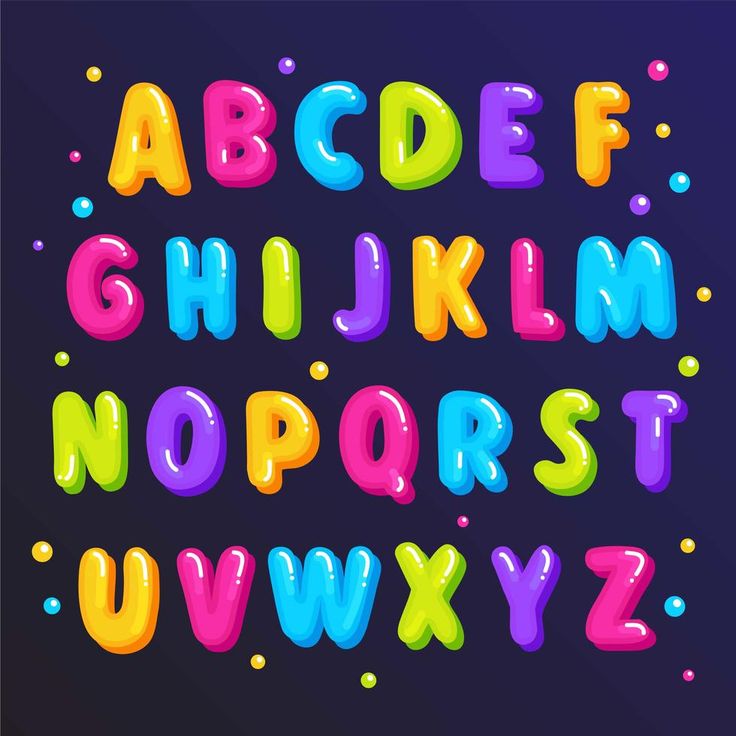
Шрифты цветные: Цветные шрифты для дизайна и оформления
Так что же такое «цветной шрифт»? Это термин, который все чаще появляется и начинает набирать обороты, однако, несмотря на использование в крупных дизайн-проектах он все еще находится в зачаточном состоянии.
Такие производители как Тypekit от Adobe уже начали выпускать некоторые цветовые варианты шрифтов с поддержкой браузера, так что есть некоторое движение в сторону их более широкого использования. Некоторые даже называют цветные шрифты “следующим большим событием в веб-дизайне”.
Сегодня мы рассмотрим ближе данный тренд, и решайте сами, насколько грандиозным он станет. Или наоборот не станет.
Что такое цветной шрифт?
Цветные шрифты практически являются тем, как они называются. Шрифты, состоящие из нескольких цветов, оттенков и градиентов, текстур и прозрачности. Эта шибко модная опция не просто добавляет цвет к буквам и надписям: это специфические шрифты со всеми включенными деталями.
Такие шрифтов могут включать в себя векторную графику, растровые изображения или же то и другое в самом шрифтовом файле, что, в свою очередь, может сделать эти шрифты тяжелее, чем стандартные пакеты шрифтов. Типичные примеры цветных шрифтов включают смайлики или буквы, которые содержат иконки внутри. Одноцветные шрифты в таком стиле часто называют хроматическими шрифтами, потому что они содержат только один оттенок или серый цвет.
Самая большая проблема с цветным шрифтом заключается в том, что нет никакого истинного стандарта его формата.
С другой стороны, основные игроки уже начали принимать рекомендации по использованию таких шрифтов. Mozilla (основа веб-браузера Firefox) и Adobe согласились с тем, что OpenType SVG является предпочтительным форматом; другие же все еще находятся в постоянном движении, когда необходимо прийти к нужному решению.
Как использовать цветные шрифты?
Одна из двух мыслей может возникнуть в вашей голове, когда вы впервые видите цветной шрифт:
- Вау, это ужасно!
- Круто! Я точно знаю, как это использовать!
Независимо от того, к какому лагерю вы относитесь, есть применения, которые идеально подходят для цветных шрифтов. Но вы должны использовать их в разумных пределах, ведь цветные шрифты предназначены для наиболее экономного использования.
Попробуйте цветной шрифт:
- Для техники захвата внимания для короткого слова
- Для элемента значка или логотипа
- Для кавычки перед началом длинного блока текста
- Для дерзкого заголовка в дизайне с минимальным стилем
- Фокусировка на определенном слове или словах в большом блоке текста
- Когда остальная часть дизайна слишком проста
- Когда шрифт будет вашим основным элементом дизайна
- Когда проект требует чего-то забавного и необычного, чтобы привлечь внимание пользователя
Как не использовать цветные шрифты
Существует гораздо больше способов не использовать цветные шрифты, чем вы можете себе представить.
Вы же не хотите в итоге получить мигающий и моргающий веб-сайт с подавляющим цветовым безумием 1990-х годов.
Не используйте цветной шрифт:
- С изображениями или над изображениями
- С забитым задним фоном
- Для большого количества текста
- С множеством других техник дизайна, такими как анимация: обычно одного цвета достаточно для создания визуального воздействия
- С другими новинками или специальными шрифтами
Развитие тренда
Тренд цветового шрифта начинает набирать силу у некоторых крупных игроков в типографике. Формат SVG OpenType, принятый Adobe и Mozilla, может стать инструментом и форматом, который поможет этой тенденции действительно взлетать. Adobe даже недавно добавил цветные шрифты в Photoshop, также вы могли заметить некоторые эмодзи в палитре символов.
Вот как Adobe объясняет OpenType SVG:
«OpenType-SVG — это формат шрифта, в котором шрифт OpenType имеет все или только некоторые его глифы, представленные в качестве изображения SVG.
Это позволяет отображать несколько цветов и градиентов в одном глифе. Из-за этих особенностей мы также ссылаемся на шрифты OpenType-SVG в качестве «цветных шрифтов».
«Шрифты OpenType-SVG позволяют показывать текст с графическими качествами, сохраняя при этом возможность редактировать, индексировать или искать. Они также могут содержать функции OpenType, которые допускают замещение глифа или альтернативные стили глифа».
«Цветные шрифты, такие как Trajan Color Concept и EmojiOne Color, будут отображаться так же, как и обычные шрифты в меню шрифтов ваших программ, но они могут не отображать весь свой потенциал, поскольку многие программы еще не имеют полной поддержки цветовых компонентов. Если ваша программа не поддерживает оформление SVG в шрифтах, глифы возвращаются к простому черному стилю. Цвет может быть применен к этому резервному стилю, поскольку он будет работать как обычный шрифт OpenType.»
Попробуйте цветной шрифт
Если цветные шрифты — это ваша вещь, вы можете либо загрузить цветной шрифт, чтобы начать работу, либо создать свой собственный, в зависимости от типа проекта над которым работаете.
Создайте свой собственный шрифт
Тип цветного шрифта, который вы создаете, на самом деле, зависит от ваших навыков работы с программным обеспечением. Цветной шрифт может включать в себя что угодно: от изображений и ваших любимых фотографий до красивых пузырей и штрихов в градиентных цветах. Вы можете сделать это самостоятельно или использовать инструмент, который поможет создать собственный цветной шрифт.
К примеру, вы можете использовать, Fontself — это дополнение Adobe Illustrator и Photoshop, которое помогает создавать пользовательские цветовые шрифты.
Скачайте или добавьте
Есть некоторые довольно классные цветные шрифты, которые кричат, чтобы вы использовали их в вашем проекте сегодня. Вот несколько шрифтов, чтобы ускорить ваш творческий поток, плюс ссылки на другие цветные шрифты, используемые выше:
- Type with Pride
- Beach Towel
- Bungee
- Watercolor Font
- Bixa Color
- Kids Toys
- OneLine Bold
- Guru
- Neon
Вывод
Готовы ли вы перейти к тренду цветных шрифтов? Или же это слишком для вас и пятнистое содержание — реальная проблема для ваших проектов?
Некоторые дизайнеры считают, что эта тенденция очень интересна и имеет реальное практическое применение в печатных проектах, таких как плакаты или листовки.
Тем не менее, они еще не совсем убеждены в ней, когда речь заходит о веб-проектах. Только время покажет, действительно ли эта тенденция стала «следующей большой вещью в веб-дизайне» или очередной мимолетной причудой.
Источник
App Store: Цветные шрифты для Клавиатуры+
Описание
Свыше 170+ шрифтов, 3000+ символов и самых разных иконок Emoji, Kaomoji. Скачайте Цветные Шрифты для Клавиатуры прямо сейчас, чтобы сделать общение ещё ярче и эмоциональнее.
А как на счёт стильных разнообразных тем для клавиатуры? Они создадут особую атмосферу для любых диалогов. Теперь общаться с друзьями ещё веселей!
► А как насчёт свыше 3000 кавайных иконок и японских Каомодзи (Kaomoji)?
► Попробуйте одну из наших стильных экранных клавиатур или пользуйтесь классическим вариантом в сдержанных тонах
► Только у нас! Поддержка русского языка в преобразовании набранного текста в заданный стиль, прямо в сообщении.
Не надо никаких дополнительных операций. ► Все иконки и шрифты можно использовать в сообщениях и комментариях в Facebook и Instragram. Хотите ещё больше фолловеров и ярких комментариев для друзей?
Не теряйте времени даром, получите свыше 170+ классных шрифтов, 3000+ символов, Каомодзи в своё распоряжение — прямо сейчас!
Примечания:
• Для разблокировки всех тем Kaomoji и клавиатуры требуются внутриигровые покупки.
Версия 3.1
Поддержка последних моделей iPhone
Оценки и отзывы
Оценок: 2
здорово!
и꙼̈н꙼̈т꙼̈е꙼̈р꙼̈е꙼̈с꙼̈н꙼̈о꙼̈!꙼̈
Норм
Приложение норм
Разработчик Cool GamApp Limited указал, что в соответствии с политикой конфиденциальности приложения данные могут обрабатываться так, как описано ниже.
Сбор данных не ведется
Разработчик не ведет сбор данных в этом приложении.
Конфиденциальные данные могут использоваться по-разному в зависимости от вашего возраста, задействованных функций или других факторов. Подробнее
Информация
- Провайдер
- Cool GamApp Limited
- Размер
- 241,5 МБ
- Категория
- Развлечения
- Возраст
- 4+
- Copyright
- © Cool Gamapp Limited
- Цена
- 1 690,00 ₽
- Поддержка приложения
- Политика конфиденциальности
Другие приложения этого разработчика
Вам может понравиться
цветных шрифтов — готовьтесь к революции!
Color Fonts — Готовьтесь к революции! цветных шрифта.
wtf
Цветные шрифты! ВТФ?
¶ Что такое цветные шрифты?
¶ Что внутри?
¶ Где подвох?
¶ Где я могу их использовать?
¶ Где взять?
¶ Как сделать цветные шрифты?
Что такое цветные шрифты?
A
Стандартный векторный шрифт
Цветной векторный шрифт.
Цветной растровый шрифт. Благодаря новым форматам шрифтов цветные шрифты наконец-то становятся реальностью для миллионов творцов.
Цветные шрифты могут влиять на любой тип текста, поскольку они могут содержать символы любого типа, включая смайлики и значки.
Обратите внимание, что цветные шрифты иногда называют хроматическими шрифтами, что на самом деле немного точнее, поскольку они могут включать многоцветные, серые или даже одноцветные символы.
⇑
Что внутри цветных шрифтов?
Файл цветного шрифта на самом деле представляет собой обычный файл шрифта, который включает дополнительные данные для отображения большего количества графических свойств, чем формы контуров символов.
Цветные шрифты теперь обычно хранятся в виде данных SVG внутри файлов шрифтов OpenType. Этот формат SVG (масштабируемая векторная графика) может содержать векторные фигуры с цветом или градиентами, а также может включать растровые изображения, что приводит к созданию растровых шрифтов.
Таким образом, цветные шрифты теперь официально называются шрифтами OpenType-SVG .
Простой. Верно?
Хорошо, реальность немного сложнее…
#TimeForSomeHistory 😉
Формат шрифта OpenType-SVG изначально был разработан Mozilla & Adobe и стал отраслевым стандартом в начале 2016 года, когда другие крупные игроки, включая Microsoft и Google договорились о едином формате для поддержки цветных шрифтов.
Все они (включая Apple) ранее разработали и внедрили свои собственные цветовые форматы для отображения смайликов в своих операционных системах, в то время как многие другие компании создали другие технологии пользовательских цветных шрифтов для игр, видео или полиграфии.
В настоящее время существует четыре основных формата цветных шрифтов , которые подходят для обычных файлов шрифтов: SBIX, COLR, CBDT и SVG, каждый из которых имеет свои особенности. Прочитайте полную историю здесь или проверьте это упрощенное резюме:
| Вектор | Растровое изображение | Штатная поддержка | |
|---|---|---|---|
| W3C SVG | ✔ | ✔ | macOS 10.14+, iOS 12+, Windows 10+ |
| Apple SBIX | ✔ | macOS и iOS | |
| Google CBDT | ✔ | Андроид | |
| ЦВЕТ Microsoft | ✔ | Windows 8.1+ |
Из-за различий и несовместимости этих форматов индустрия дизайна переживает переходный период, в течение которого может потребоваться несколько форматов цветных шрифтов для обеспечения кросс-платформенной совместимости в нескольких операционных системах, браузерах и приложениях.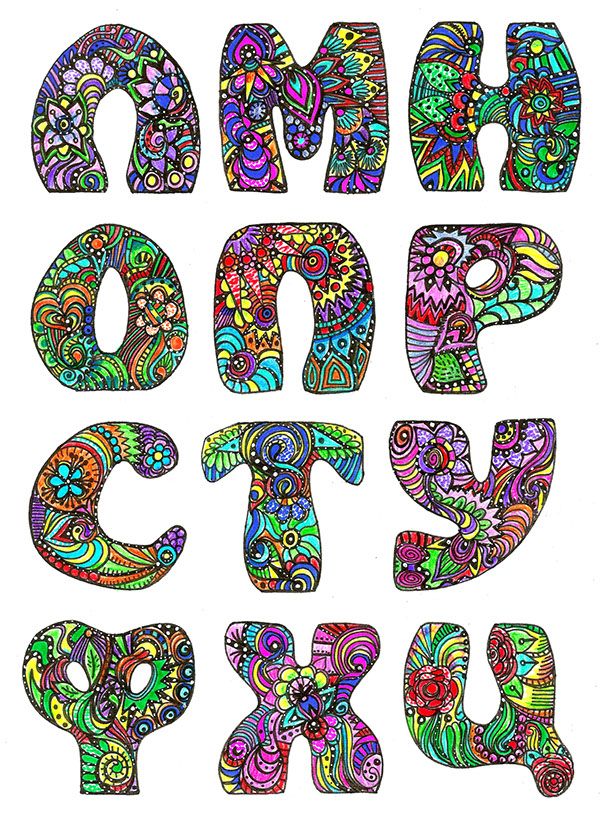
Но OpenType-SVG, кажется, имеет все шансы стать золотым стандартом теперь, когда шрифты OpenType-SVG поддерживаются тремя операционными системами. : Windows 10, macOS Mojave и iOS 12. Цветные шрифты также могут включать некоторые альтернативные данные векторной формы в качестве резервного решения для программного обеспечения, которое (пока) не поддерживает ни один из встроенных цветовых форматов.
⇑
Где подвох?
Как насчет размера файла?
Файл цветного шрифта обычно больше, чем файл обычного шрифта, и намного больше, если шрифт содержит символы растрового изображения с высоким разрешением.
В то время как шрифты обычно весят от десятков до нескольких сотен килобайт, цветные векторные шрифты могут весить от сотен килобайт до пары мегабайт в зависимости от их визуальной сложности.
Цветные растровые шрифты могут иметь размер от нескольких мегабайт до десятков мегабайт, а размеры увеличиваются, когда в один файл встраиваются несколько форматов цветных шрифтов.
Как насчет масштабируемости текста?
Хороший вопрос! Цветные шрифты на основе векторных глифов можно изменять без потерь, как и любой обычный шрифт.
Масштабированный цветной векторный шрифт
Масштабированный цветной растровый шрифт
Цветные растровые шрифты, как и любые другие фотографии или пиксельные изображения, будут корректно масштабироваться до определенного размера в зависимости от исходного разрешения. За пределами этого разрешения надпись будет выглядеть пиксельной.
Таким образом, независимо от того, печатаете ли вы текст цветным растровым шрифтом или отображаете его на экранах с высоким разрешением, вам придется проверить, до какого размера он может правильно масштабироваться.
Поскольку цветные растровые шрифты будут использоваться в таких разных контекстах, как Интернет или печать, дизайнерам потребуется несколько версий файлов растровых шрифтов, с полноразмерными изображениями для редактирования на рабочем столе и уменьшенными версиями для Интернета.
⇑
Где можно использовать цветные шрифты?
Теперь, когда OpenType-SVG принят в качестве отраслевого стандарта, есть большая вероятность, что вы сможете начать использовать цветные шрифты в своем любимом программном и аппаратном обеспечении.
Мы постоянно обновляем список приложений и браузеров, поддерживающих цветные шрифты. Вот так:
- 😀 Да, цветные шрифты поддерживаются
- 😐 Да, с ограничениями
- 😢 Нет
Приложения
| Цветные шрифты | Поддерживаемые форматы | Комментарии | |
|---|---|---|---|
| Фотошоп | 😀 | СВГ SBIX | |
| Иллюстратор | 😀 | СВГ SBIX | |
| InDesign | 😀 | СВГ SBIX | |
| QuarkXPress | 😀 | SVG SBIX ЦВЕТ | |
| Пиксельматор | 😀 | СВГ SBIX | |
| Эскиз | 😀 | СВГ SBIX | |
| Affinity Designer | 😀 | СВГ | |
Paint. NET | 😀 | СВГ | |
| Adobe XD | 😢 | ||
| Премьер Про | 😢 | ||
| After Effects | 😢 |
Веб-браузеры
| Цветные шрифты | Поддерживаемые форматы | Комментарии | |
|---|---|---|---|
| Microsoft Edge | 😀 | SVG SBIX ЦВЕТ CBDT | |
| Сафари | 😀 | SVG SBIX ЦВЕТ | |
| Firefox | 😀 | SVG ЦВЕТ | |
| Хром | 😢 | ЦВЕТ CBDT | |
| Internet Explorer | 😐 | ЦВЕТ | |
| Опера | 😐 | ЦВЕТ |
⇑
Где взять цветные шрифты?
Цветные шрифты все еще довольно редко встречаются в наши дни из-за их новизны.
Но вам повезло, потому что мы начали собирать классные цветные шрифты:
Gilbert от Type With Pride
Popsky от Игоря Петровича
MEGAZERO от Alex Trochut
Aires от Yai Salinas
Abelone от Maria Grølund
Playbox от Matt Lyon
Bixa Color от NovoTypo и Roel Nieskens
Bungee color от David Jonathan Ross
OneLine Bold от Roman Kaer 9000 5